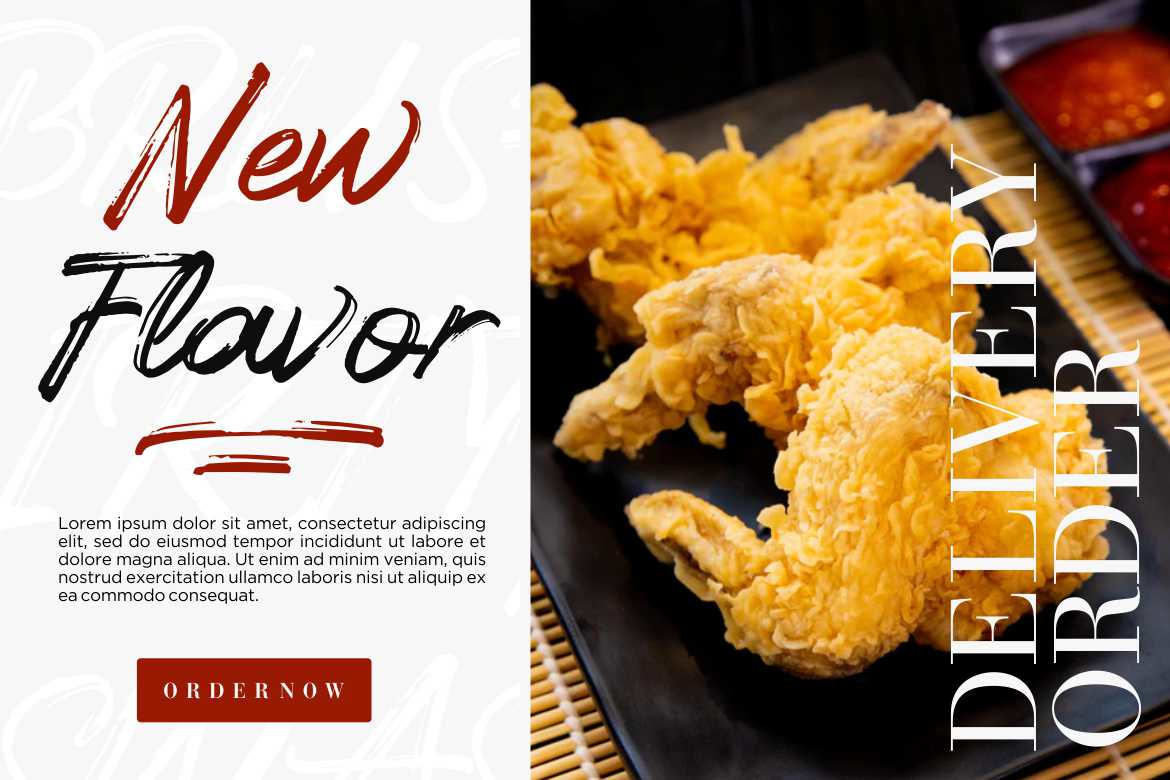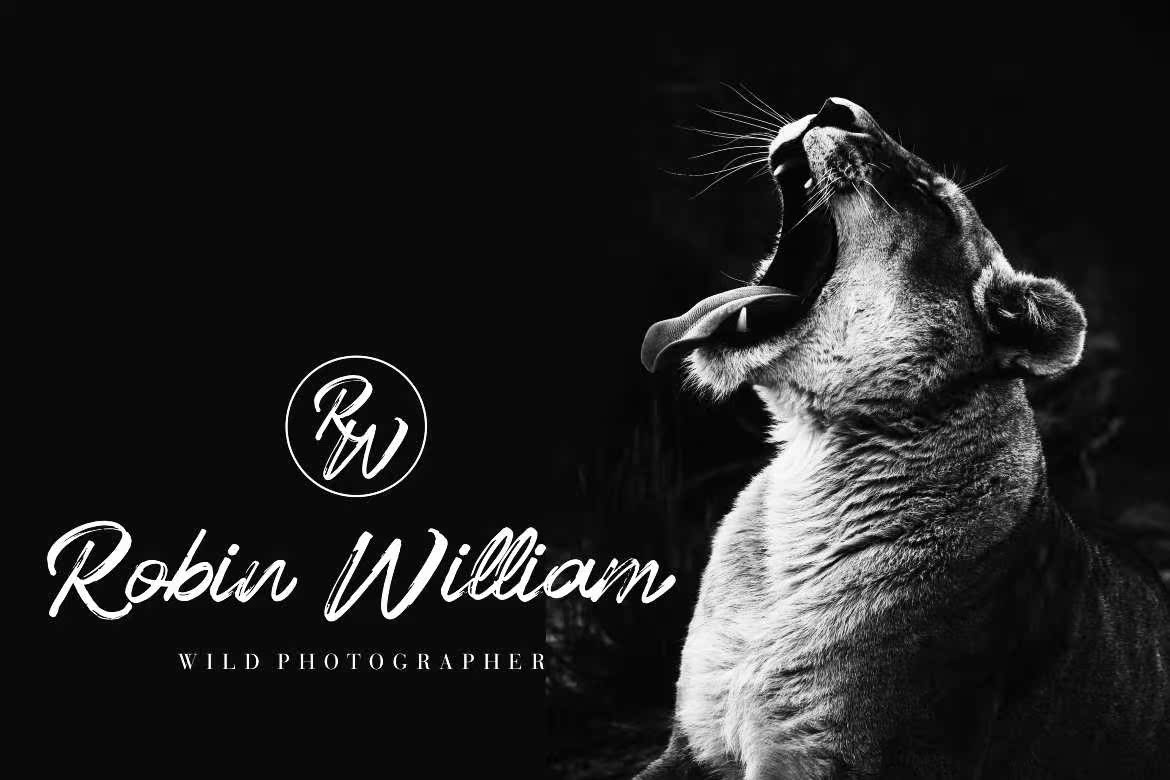
CrunchyFont是随意且快速编写的画笔脚本。此纹理非常详细。您可以使用此字体中的替换画笔。CrunchyFont适用于徽标、衬衫、时尚、博客、网站、产品品牌、海报、传单、任何打印模板或背景图片。如何替换,如果您使用Adobe/CorelDraw,您只需将其中一个字母/数字(用于清洗)和一个狭义字符显示在文字下方,您可以使用可选字符替换。可选字符Ready用于“f,g,j,Yandnumeral 0–9“CrunchyFont是一款随意且快速编写的画笔脚本。此纹理非常详细。您可以使用此字体中的可选画笔。CrunchyFont适用于徽标、衬衫、时尚、博客、网站、产品品牌、海报、传单、任何打印模板或任何背景图像。如何替换,如果您使用Adobe/CorelDraw,您只需将其中一个字母/数字(用于清洗)和一个狭义字符显示在文字下方,您可以使用可选字符替换。可选字符Ready用于“f、g、j和D数字0–9”